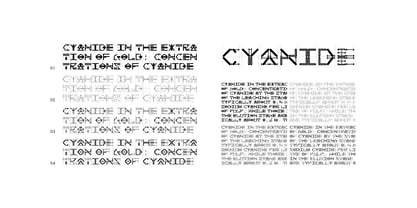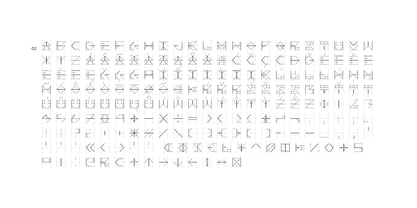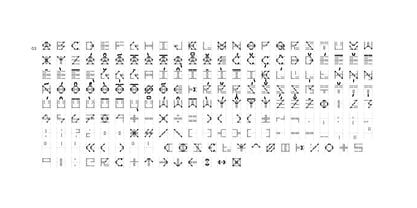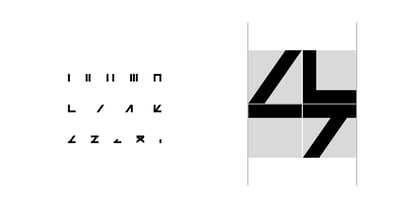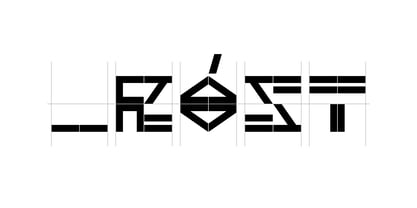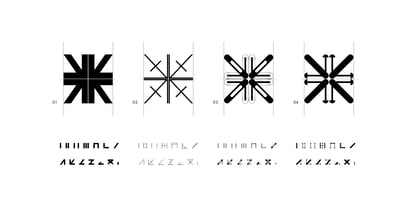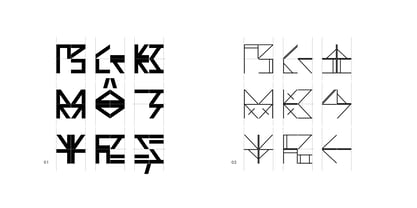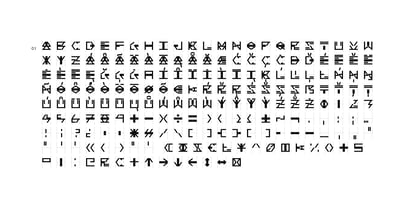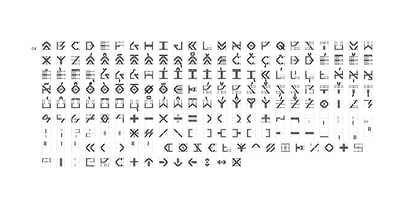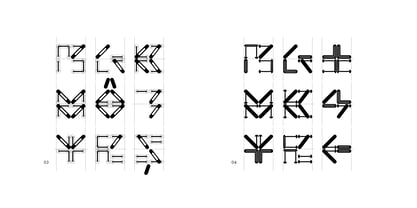
4444 Modular
by Luis Rutz
The 4444 Modular Font Family was designed by Luis Rutz and published by Luis Rutz. 4444 Modular contains 4 styles and family package options.
4444 Modular besteht aus nur 14 Elementen und kann so schnell manipuliert werden. Der Zeichensatz basiert auf einem einfachen 4×4-Raster und ist in vier Varianten verfügbar.